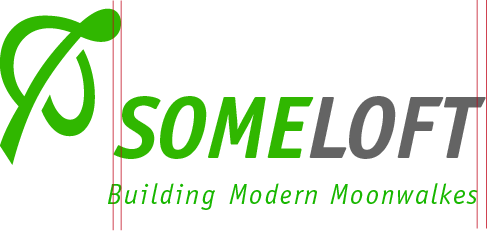
Logodesign: kursive Schrift vertikal richtig setzen
ich stehe vor einem Problem. Ich möchte das Logo einer Firma verbessern, da ich mit der Ausfertigung der Marketing-Agentur nicht zufrieden bin.
Da ich gefühlte Jahrhunderte nichts mehr in der Typografie gemacht habe, brauch ich Eure Meinung, bzw. Hilfe. Das große Problem, vor dem ich stehe sieht wie folgt aus:
Das Logo besteht aus drei Blöcken: Vektorgrafik, Firmenname in Versalien, fett, und kursiv; Zusatzclaim in kursiv und extrem gesperrt. Ich habe Euch mal einen Dummy gemacht, wo Ihr die Problematik gut erkennen könnt. Der Dummy mit den Linien zeigt, wo die einzelnen Blöcke positioniert sind. Es ist dem Originial exakt nachempfunden in der Spationierung, Durchschuss, Wortlänge, Sperrung etc.
Wie setze ich nun kursive Texte, die dazu noch unterschiedlich groß, fett, Schriftschnitt sind in der Vertikalen richtig, so dass es harmonisch ist?
Meine ersten Schritte wären:
1. den Abstand zwischen den beiden Blöcken verringern
2. die Schriftgröße des Claims größer, dafür die Sperrung verringern
Aber mein Problem ist, wo soll der Claim genau anfangen und wo genau aufhören?
Ich denke hier gibt es keine "Regel" die richtig ist, nur eine optisch stimme Lösung.
Im Grunde hast du 2 Möglichkeiten:
Entweder die Unterziele klar an der Hauptzeile orientieren und eine kompakte Form herstellen: dann würde die Zeile etwas nach oben rücken, das B ziemlich genau da stehen lassen wo es jetzt steht, und die Unterzeile etwas verkleinern, bis sie sich optisch an der Senkrechte (nicht dem Querbalken!) des T orientiert. (Das ist ja das "verschärfte" Problem in diesem Beispiel: Kursiv und ein Versal-T.)
So bekommst du einen kompakten Textverbund, der nicht ausfranst. Den dann nach rechts ausschweifenden Balken des T ist der Seher gewohnt, das macht jedes T so und ist somit "etabliert".
Oder du machst einen deutlicheren Unterschied in der Breite der beiden Zeilen – dann ist die Unterzeile ein Zusatz, kein Teil des Logos mehr, und braucht keinen direkten Bezug mehr.
Nur das "Dazwischen" ist schwierig, da es immer so aussieht als wäre ungenau gearbeitet worden.
Vielen Dank für Deine Antwort und die Ausführungen. Ja, dieses kursive Versal-T ist tatsächlich mein größtest Problem. Aber Deine Ausführungen haben mir gezeigt, dass ich auf den richtigen Weg bin. Mir ist klar, dass es nicht "die einzige Lösung" überhaupt gibt.
Und ich denke, ich werde es auch so machen, wie Du es beschrieben hast, da der Zusatz (leider) zum Logo gehören soll. Mir würde es ohne besser gefallen - aber naja.